Les dispositifs d’identification, de reconnaissance de signes et de codage sont des constantes de l’espèce humaine, si ouverte d’apparence et si secrète dans ses pratiques. C’est aussi une partie du travail de l’auteur depuis des décennies.
Du paradoxe qui réside dans l’utilisation de moyens identiques pour communiquer ouvertement ou en se masquant, nous avons cherché à savoir si, dans la suite de signes qui forment les alphabets, se trouve une influence, voire une intention.
Un travail sur l’histoire des alphabets.
De très grandes civilisations nous sont connues par leurs magnifiques constructions, celles des Mayas et des Khmers par exemple, ou par leurs tombeaux énigmatiques qui recèlent des bijoux et des artefacts fascinants, comme celles des Nordiques ou les Celtes.
D’autres sont glorifiées par les immenses légendes, racontées puis écrites, qui définissent des genèses, des sagas, des panthéons, des gestes héroïques, des doctrines et des modes de pensée et de vie.
L’une d’elles est particulière car elle remplit tous les critères imposés pour le passage à la postérité : les constructions, les rites, les écrits, les belles histoires, une pensée structurée, des techniques civiles et militaires imposantes, une médecine bien documentée et une bonne cuisine.
Il n’est pas très difficile d’identifier quel peuple a si bien propagé sa culture que son influence se fait sentir près de 6000 ans plus tard, ce sont bien sûr les Égyptiens.
Et pour l’écriture ? C’est compliqué.
Bien qu’elle ne leur soit pas exclusive, nous associons l’écriture hiéroglyphique à l’histoire de l’Égypte antique, depuis ses débuts jusqu’à sa mise à l’ombre vers l’an 350 de notre ère.
L’un des grands mystères à éclaircir concerne l’emploi de leur écriture, car les Égyptiens n’ont pas, au faîte de la gloire des Ramsès, vers – 1 200, normalisé et imposé leurs expressions culturelles.
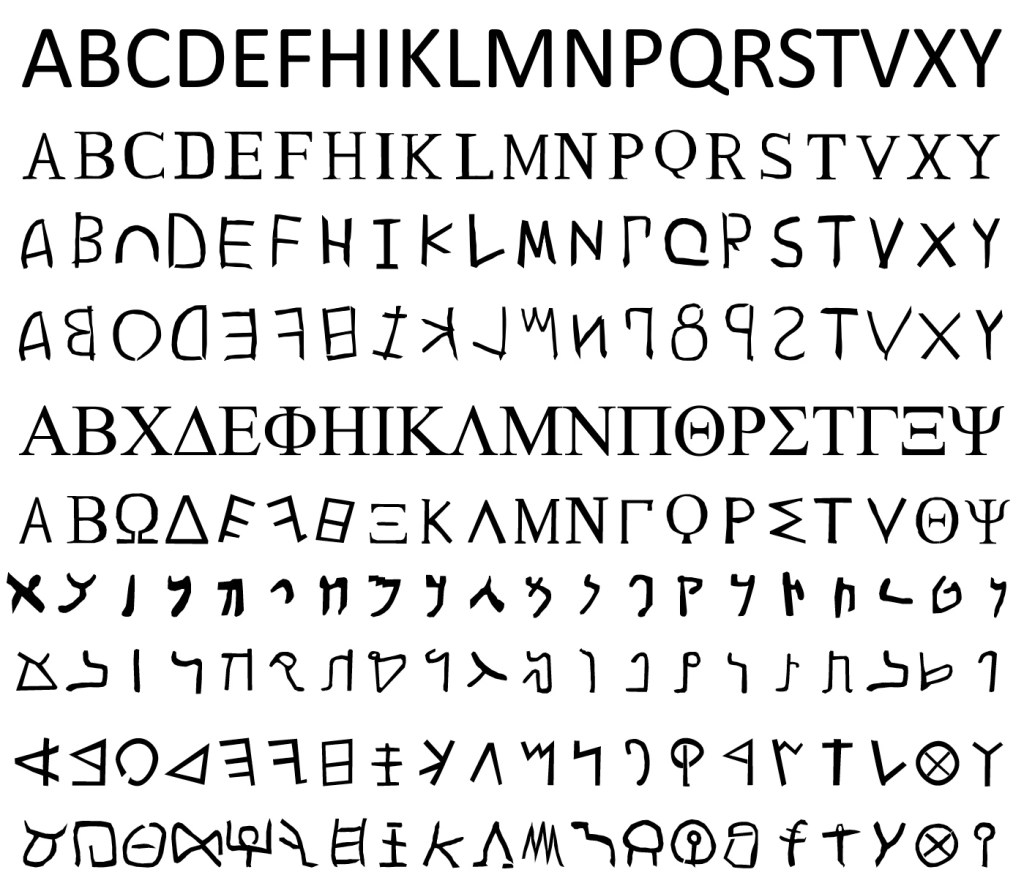
C’est étrange. Ont-ils été tentés de le faire avant de renoncer face à l’hostilité des peuples dominés ?
Étaient-ils si conscients de l’avantage que leur conférait un système complet, sur les plans militaires et administratifs, face à des peuples si peu pourvus dans ces domaines, qu’ils ne voyaient pas l’intérêt de partager ?
Ou, au contraire, ont-ils procédé de façon si discrète et peu impérieuse que nous n’en avons pas eu conscience pendant des millénaires ?
C’est en procédant à une recherche de sens, à l’identification des signes et à l’analyse de la logique ancestrale, que nous découvrons que des hiéroglyphes se sont glissés jusqu’à nous, en mode furtif.
Ils sont présents dans nos vies scripturales, au point de formater la plupart des alphabets utilisés de nos jours par pas loin de quatre milliards de personnes sur la Planète.
Quand et pour quelles raisons, cette infusion culturelle a-t-elle eu lieu ?
C’est précisément ce que nous vous présentons ici, en vous racontant l’origine de ces « lettres données » qui constituent le « Code Egyptien ».
Elle commence, ce qui est logique, par une genèse !